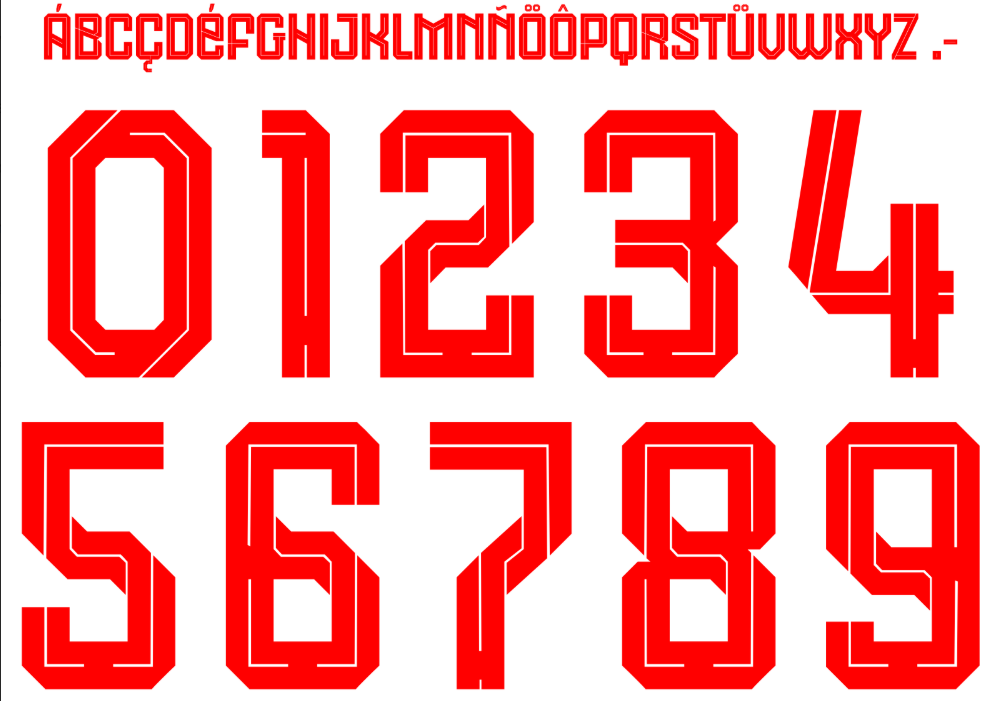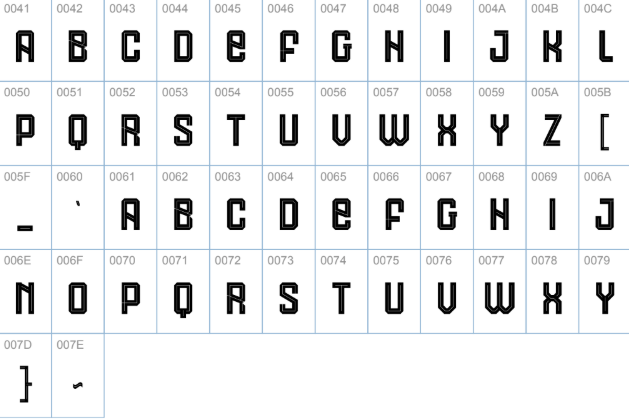
O Dinamo București, um dos clubes mais tradicionais e apaixonantes da Romênia, entra na temporada 2025/26 renovando sua identidade visual nos gramados. A parceria contínua com a fornecedora italiana Macron resultou em uniformes que misturam a clássica cor vermelha dos “Câinii Roșii” (Cães Vermelhos) com tecnologias modernas de tecido e design.
Um dos pontos altos dos novos kits é, sem dúvida, a tipografia utilizada nas costas das camisas. Fundamental para a estética do uniforme, a fonte escolhida pela Macron para esta temporada oferece clareza e um visual arrojado, essencial para competições de alto nível na Liga I Romena. Se você é designer, editor de patches para games ou colecionador digital, ter essa fonte em sua biblioteca é indispensável para criar projetos fiéis à realidade.
Neste artigo, apresentamos todos os detalhes e o link para download da fonte Dinamo Bucuresti 2025 – 26, uma renderização inspirada na tipografia oficial usada pelos jogadores.
Estilo visual da tipografia
A fonte desenvolvida para a temporada 2025/26 segue o padrão de excelência da Macron, conhecida por criar tipos limpos e funcionais.
- Geometria e Design: A tipografia apresenta um estilo sans-serif condensado, com bordas levemente angulares que transmitem modernidade e robustez. Diferente de temporadas anteriores que podem ter usado fontes mais arredondadas, a versão 25/26 foca na legibilidade à distância e na agressividade visual.
- Aplicação nos Uniformes: No kit titular (Home), a numeração e os nomes geralmente são aplicados em branco para contrastar com o vermelho vibrante do clube. Nos uniformes de visitante (Away) ou alternativos, a fonte se adapta em cores contrastantes, mantendo a consistência da identidade visual.
- Personalidade: O desenho da letra reflete a força do Dinamo București, combinando uma estética europeia clássica com toques de design esportivo contemporâneo.